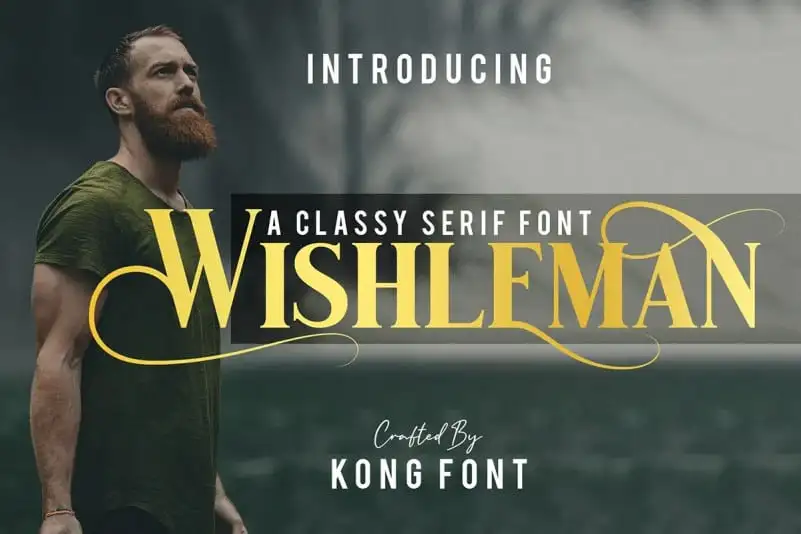
Wishleman Serif Font – Download Grátis
Olá a todos. Eu gostaria de apresentar a vocês uma nova opção para adicionar ao seu arsenal de fontes — o Wishleman Serif Font. Desenvolvido pela fontkong, esta serifa clássica é única e repleta de alternativas e ligaturas para o idioma latino padrão. Além disso, possui amplas possibilidades para headlines e uma vasta gama de aplicações, como logotipos, templates para impressão, identidade visual e muito mais. Engajada, versátil e cheia de personalidade, é um excelente complemento para qualquer projeto que exija sofisticação e elegância. Se você está procurando por uma fonte serifa com destaque em sua paleta, não perca tempo, o Wishleman Serif Font provavelmente será a escolha certa.